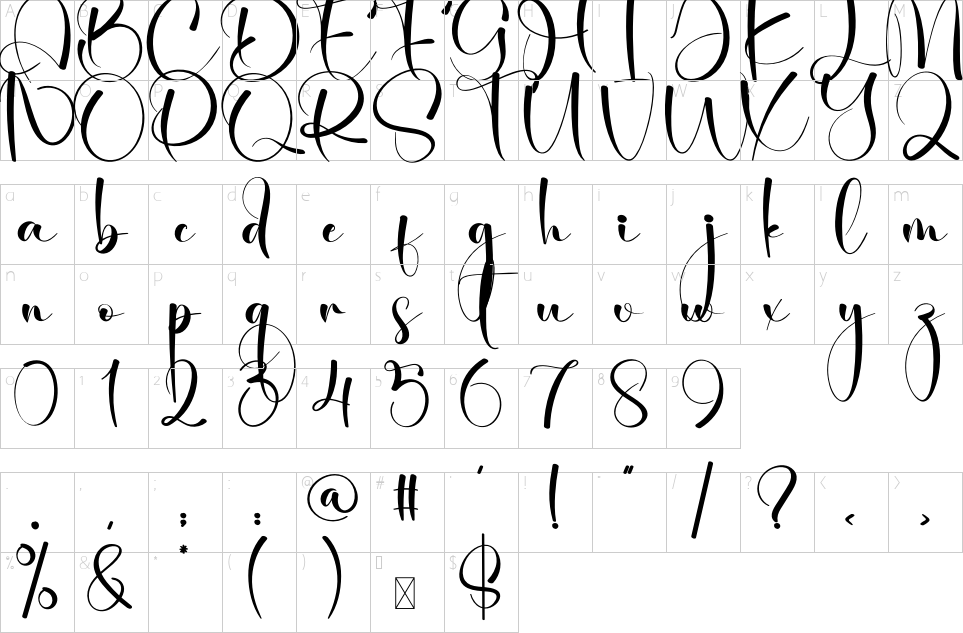
A Magnolia Font é uma fonte elegante e suave, ideal para criar designs de alto nível. Esta fonte foi projetada por scratchones e já foi baixada 296 vezes. Suave e agradável, ela combina perfeitamente com textos legíveis e bonitos, tornando-a uma opção versátil para designers de web, gráficos e até designers de aplicativos móveis. Se você está buscando um estilo de letra que ofereça um toque suave e delicado sem comprometer a legibilidade, a Magnolia é uma excelente escolha. Com seu design minimalista, ela se adapta perfeitamente a uma variedade de projetos, tornando-a uma fonte indispensável para qualquer designer.